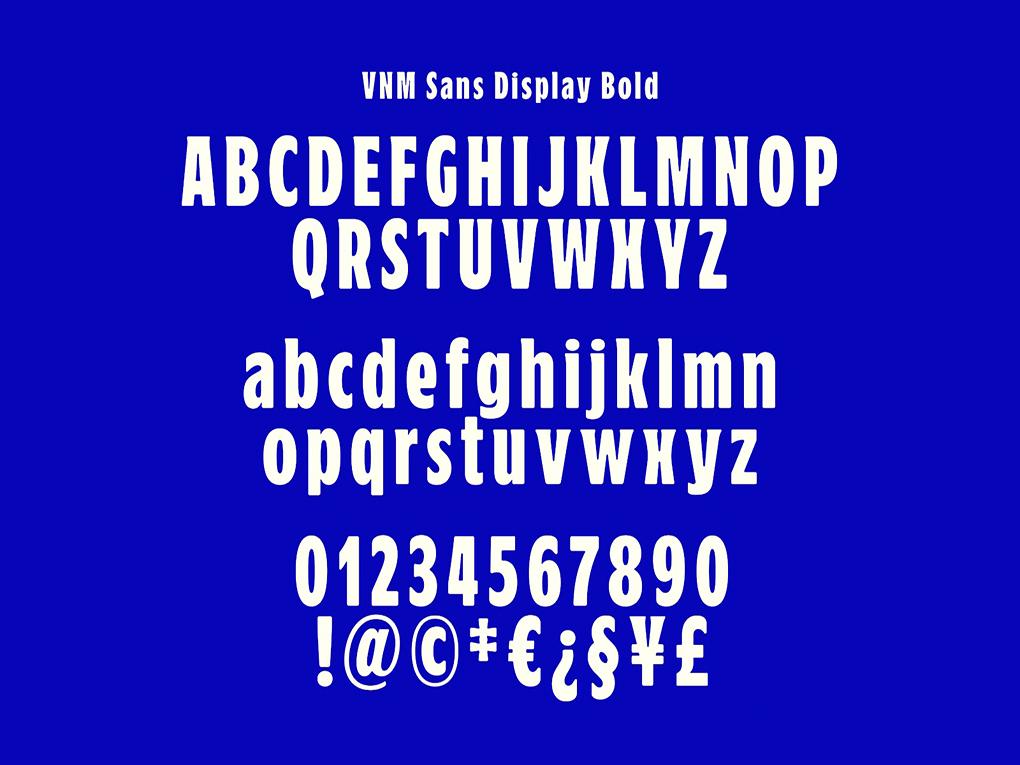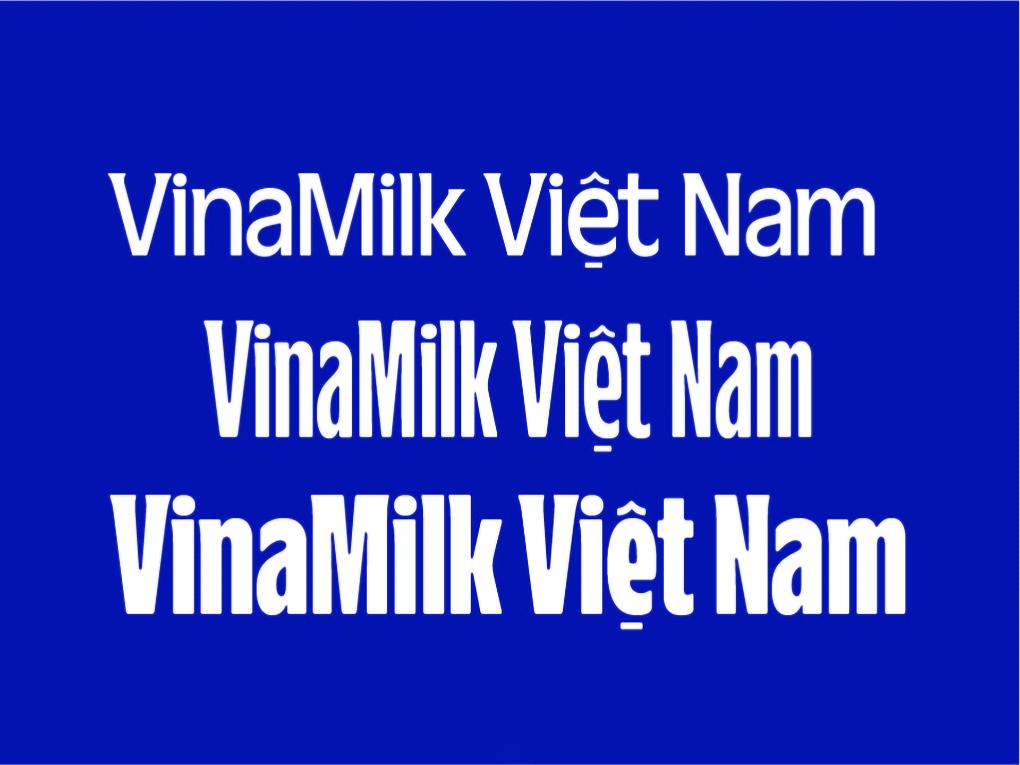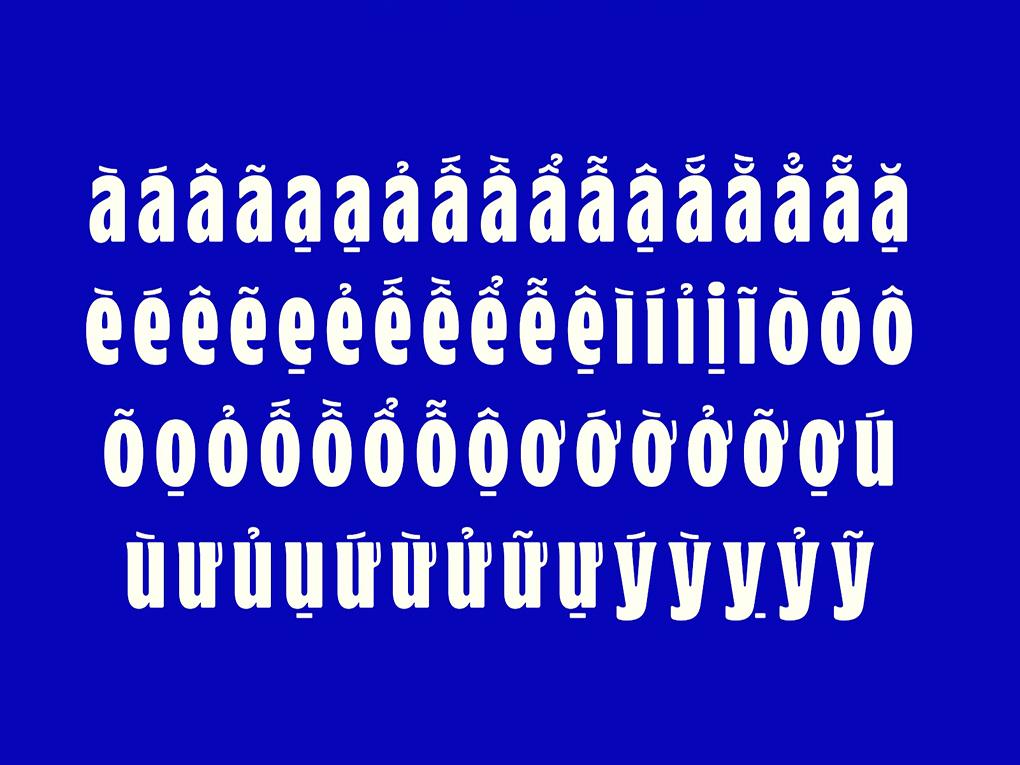
Font VNM Sans Std là gì?
VNM Sans Std là một bộ phông chữ thuộc dòng Sans-Serif kinh điển, được tối ưu hóa cho mục đích hiển thị và in ấn chuyên nghiệp tại thị trường Việt Nam. Đặc trưng của VNM Sans là sự tối giản, rõ nét và tính đa dụng cực cao, phù hợp cho mọi loại hình từ văn bản hành chính đến tiêu đề bao bì sản phẩm. Đây là lựa chọn phổ biến cho các doanh nghiệp muốn xây dựng hình ảnh thương hiệu minh bạch, hiện đại và dễ tiếp cận.
Ưu điểm vượt trội của bộ phông này là khả năng hiển thị cực tốt trên các bề mặt khó in như gốm sứ, kim loại hay vải canvas. Bản tải font VNM Sans Std việt hóa tại In Viva đã được căn chỉnh kerning tiếng Việt hoàn hảo, đảm bảo các đoạn văn bản dài trên catalogue hay hộp giấy luôn thoáng đạt và dễ đọc. Việc sở hữu phông chữ này giúp các ấn phẩm quà tặng của doanh nghiệp bạn toát lên vẻ chỉn chu và đẳng cấp.
Lưu ý: Với VNM Sans Std font, bạn nên phối hợp linh hoạt giữa các biến thể (Light, Regular, Bold) để tạo phân cấp thông tin rõ ràng trên túi giấy hoặc nhãn dán sản phẩm.
Sử dụng font chữ VNM Sans Std cần lưu ý gì?